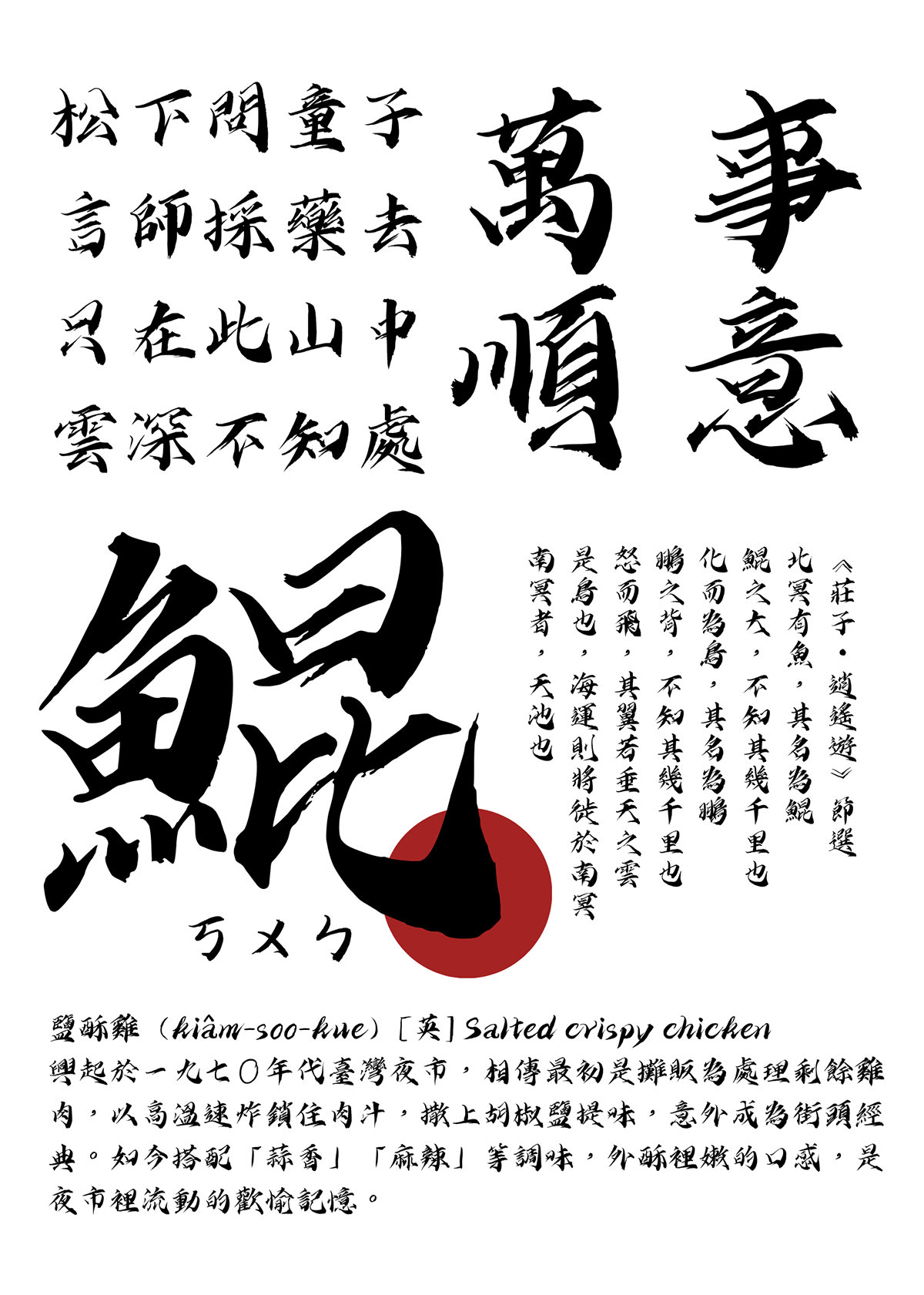
字嶼雲遊手書[字屿云游手书]字形铿锵有力,锋芒尽显,透过局部形变与笔势外拓,叠加出整体气势,兼顾阴柔与阳刚、含蓄与强劲之美。
字嶼雲遊手書[字屿云游手书]以台语常用标准汉字为标准,参考 jf7000 字集,包括注音符号、欧文字符、阿拉伯数字和标点符号,总字符约7640字以上。
注意:该字体主要为繁体字。